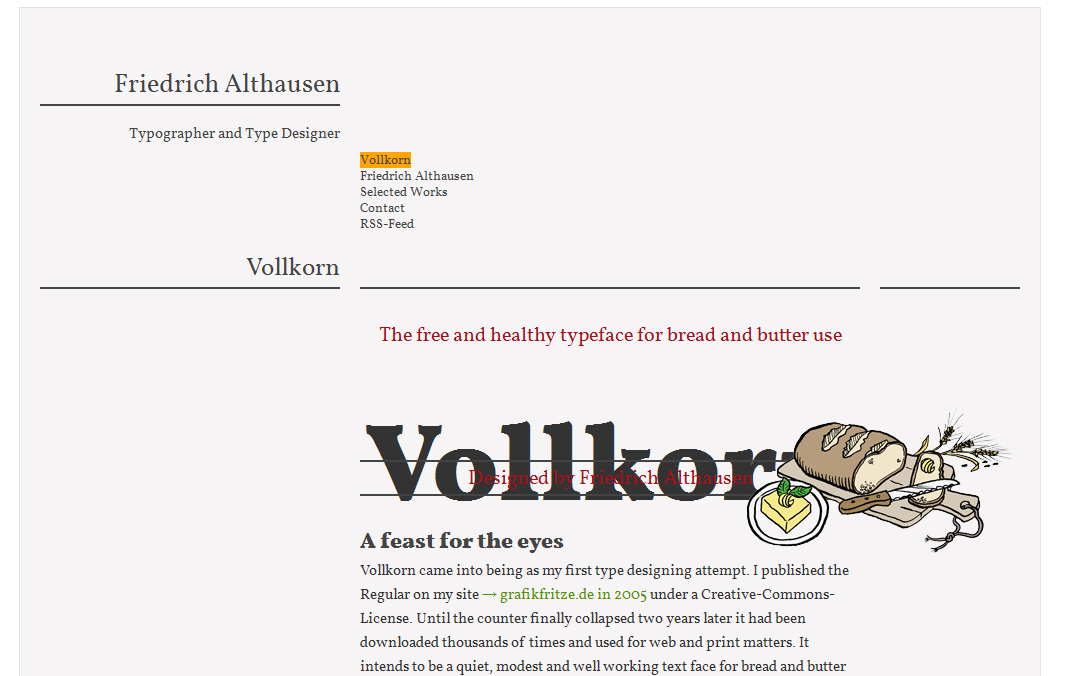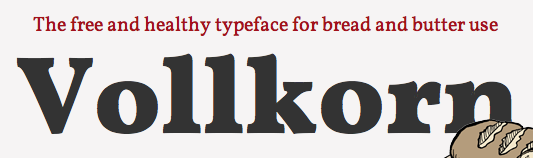
Vollkorn italic ist raus!
Wie schön :D Allerdings schreckt der Titel eher ab.
Muss da wirklich so ein riesiges Loch nach dem V sein?
Bertel, leider setzen noch nicht alle Brauser das Kerning um.
Bei mir siehts so schön aus.
Vielleicht sollte ich den Titel doch lieber als Pixelbild einbinden …
leider setzen noch nicht alle Brauser das Kerning um
Vermutlich setzt ausschliesslich Firefox das Kerning um oder Linux-Browser, die Pango verwenden. So verhält es sich jedenfalls bei den Ligaturen, wo meines Wissens Firefox auf Mac OS X derzeit alle anderen Browser aussticht.
Hier die schöne Version, extra für Bertel! :huhu:
So soll er aussehen!
Nö, in Safari geht das auch.
Das habe ich nicht gewusst – vielen Dank für den Hinweis! Damit funktionieren auch in Safari und Chrome die Ligaturen ein bisschen, wenn auch noch nicht so vorbildlich wie in Firefox. Bedauerlich nur, dass es kein valides CSS ist.